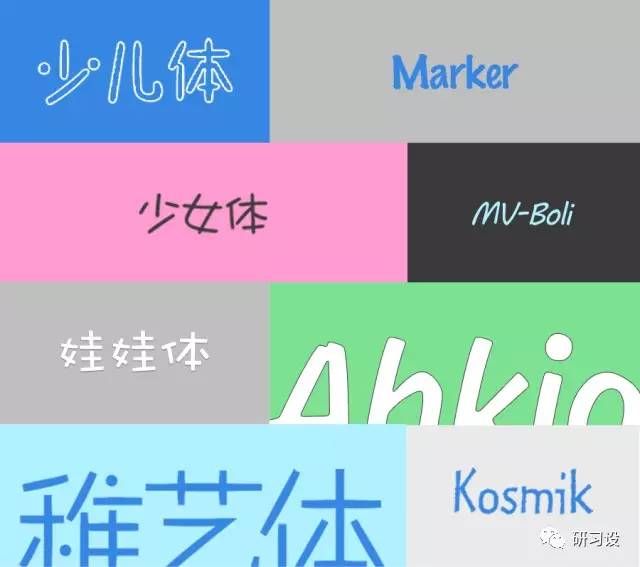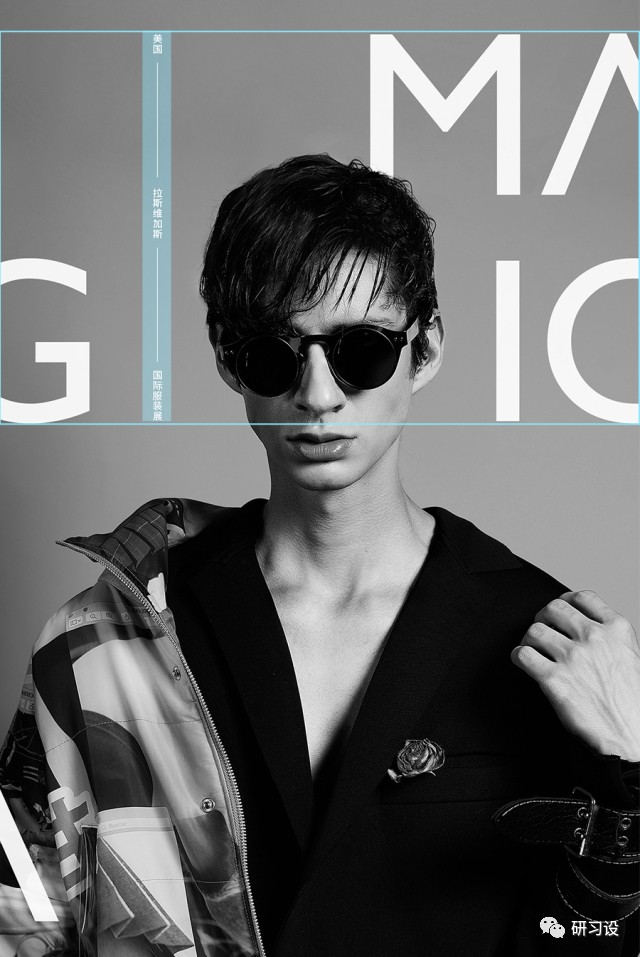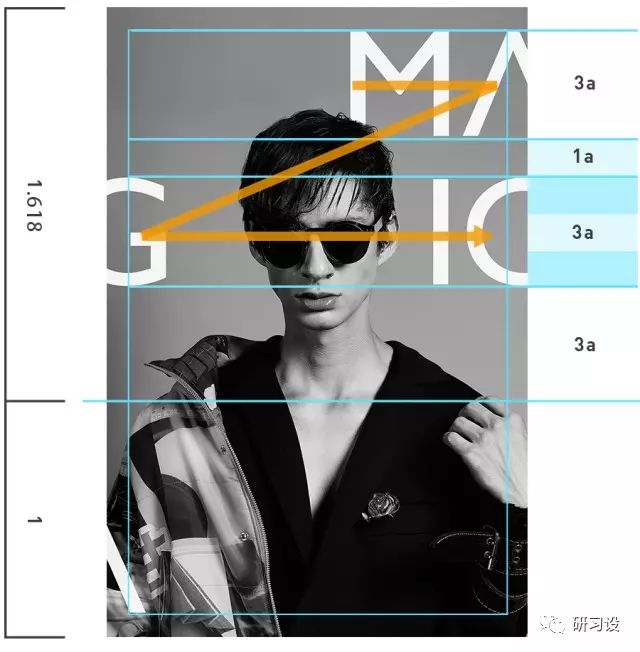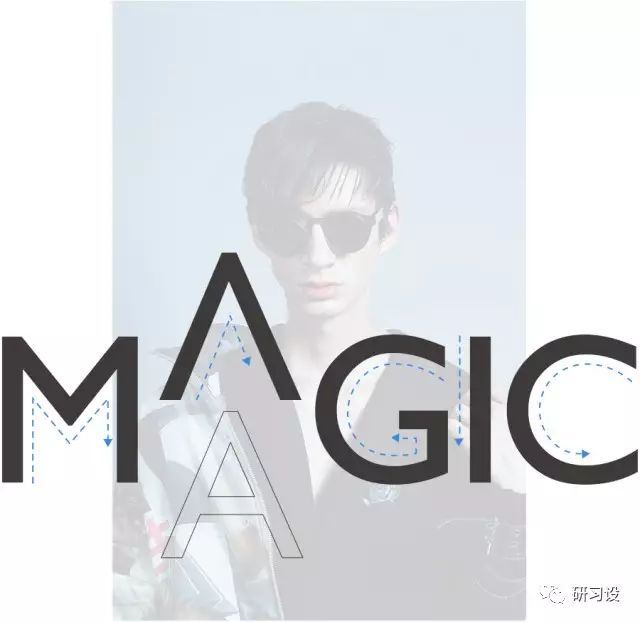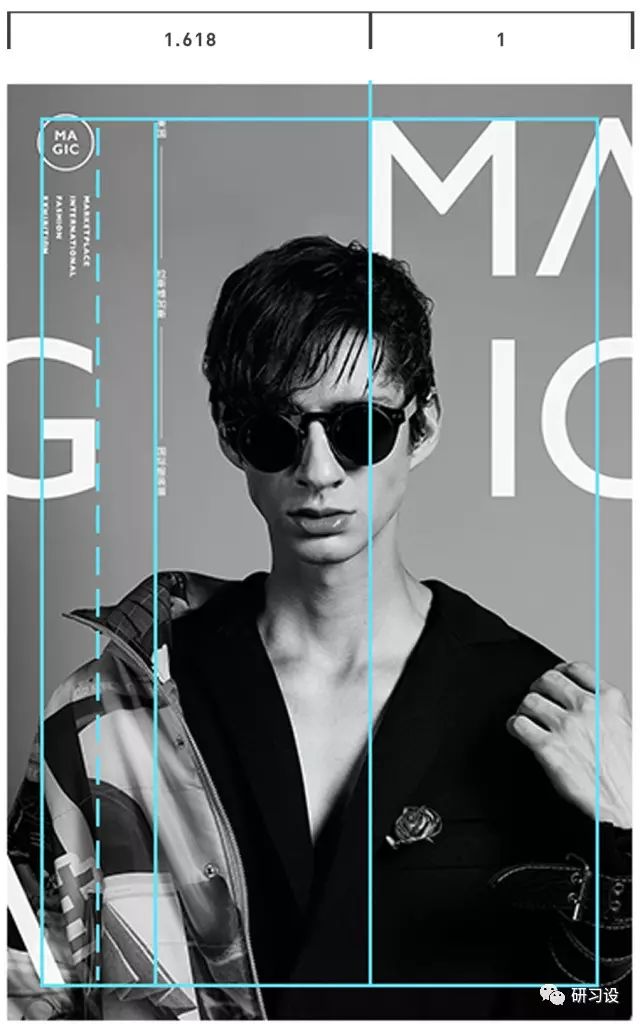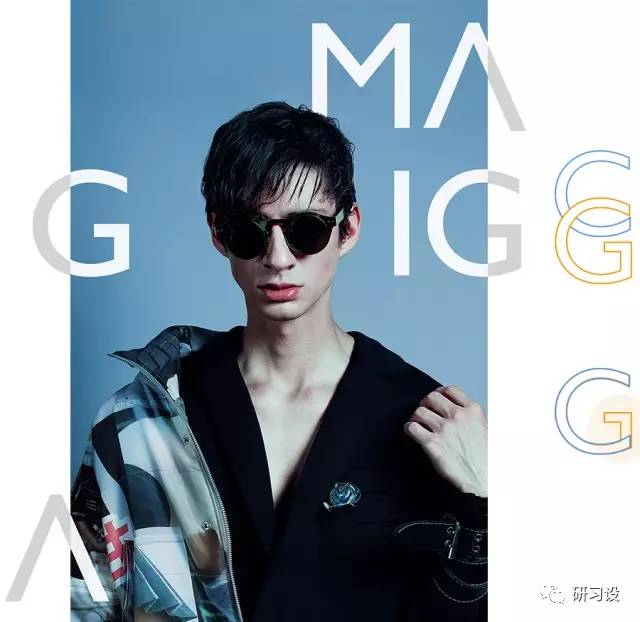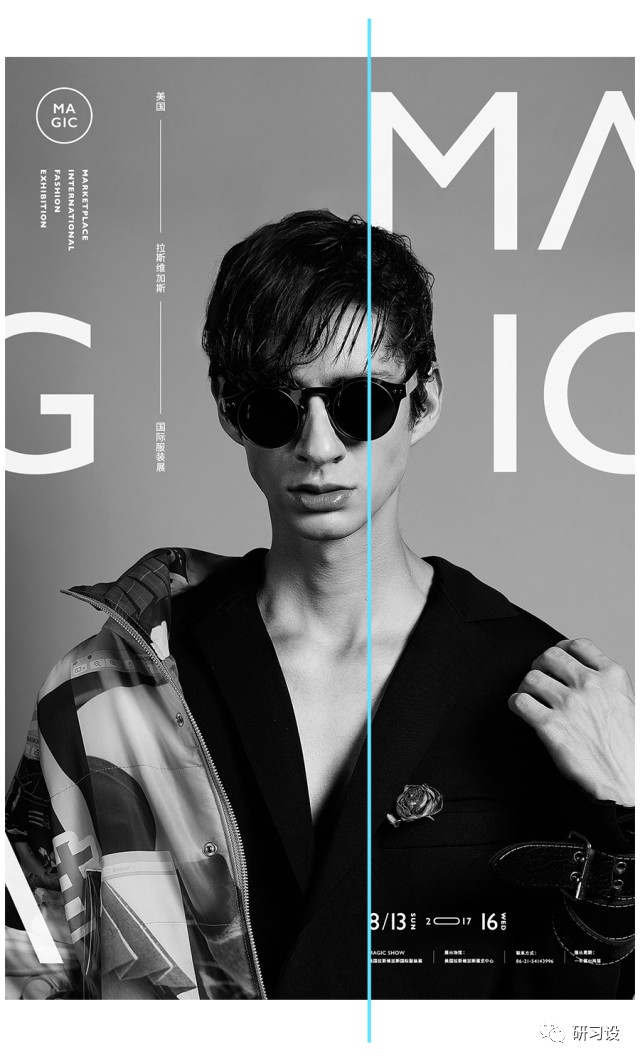
如何搭配字体?一篇文章教你轻松学会搭配字体
每一种字体都有其不同的面貌与适用情境,拿电影举例,古装电影除需要演员的服装与场景符合情境外,配乐与字体也都需要统一风格,以符合特定时代背景的整体氛围。设计亦是如此,本期将为大家介绍字体的大致分类以及不同情境下适合表现的字体有哪些。
其中我们会试图解释为什么这种字形会给人这样的印象,以及对大分类下的字体进一步细分,如:不同的黑体在气质表现上都有哪些区别?它的应用场景有哪些?想要知道这些疑问的话,就请继续往下观看吧!
字体的分类其实并没有一个官方的标准,但各种分类方式的基本原则是相同的,这里为了方便理解,将西文与汉字之间具有共通性的字体类别相结合对应,一共大致分为以上五类。
字体的应用场景大致来说一共有两种用途,一种是以少量字数出现的标题用字,以及大面积出现的正文用字。对于标题用字来说,更加强调易认性,字形设计往往张力较大细节较多,以达到抓眼球的目的。而针对正文的字体设计,更强调易读性,字形变化性较小,除正文用途外也可以在标题中使用,是普遍使用的字体。
与大家玩个游戏,当我们看到下方的图片时,哪些会给你想去亲近和触摸呢?又有哪些图片会让你觉得危险想远离它呢?在心中默默选择好后我们接着往下看。
在现实生活中,尖锐的钉子、刀尖、破碎的玻璃,这些都会划伤皮肤,而在大自然中,植物的尖刺与锋利的石头也同样是危险的。这些经验与记忆每时每刻都在影响我们的感受,让我们对事物产生同形联想,当人们看到这类物体,视觉心理上会产生紧张感,而外表光滑圆润的物体多数是安全无害和易于接近的。所以说,上图中能够传达亲近感与可爱印象的图片应该是编号②④⑤。
在字体中,同形联想依然存在,中文的圆体是从黑体字逐渐演化而来,结构上继承了黑体的工整大方。笔画的末端圆润,给人易于亲近的印象。随着笔画的粗细变化,字体的气质也会随之变化,粗笔画的圆体字会呈现出儿童与幼稚的印象,笔画越细,则会越显成熟。
在西文字体中的圆体,也是根据无衬线体演化而来,气质的变化与中文圆体类似。因为西文的字母笔画相对于中文来说要少,结构上也更加简单,所以在粗细的变化的幅度上会较中文圆体的粗细幅度更强烈一些。
如今数码字库中的字体,就像工厂中批量生产的罐头一样,非常的规范,传递出冰冷的机械感。而人为手写的文字则因为笔画书写的不规则痕迹给人温暖自然的感觉,更加具有生命力。
想要让字体传递出亲和力,我们就需要选择具有手写特征的字体,这种字形会更具人文气息。不同的手写字体会呈现出不同的亲和力,笔画轻松自然的手写体用在休闲的情景中较为合适,像西文这种铜版手写体 ⎾ 西文花体 ⏌ 则表现的更加正式与高级。
针对表现儿童的字体,他们的共同点都是具有手写的特征,而在笔画末端多数呈现圆滑的形状。这里需要注意的是,我们不能根据自己的喜好而随意应用儿童体,对于青春期的少女或者表现小孩时,我们使用儿童体并不会有什么问题,但是如果出现在政府的对外形象或本应体现端庄的场景,就不是那么合适了。
下图中,哪些图片会给你现代的感觉?哪些又会给你自然的印象呢?仔细想想这背后的原因之后,我们继续往下看。
所谓的现代感,其实就是自然界中找不到的,人们通过解构大自然,运用几何与线条人为创造出的物体。它是符合当今时代流行的趋势的,在工业、音乐、服装、建筑等各个领域都有体现。上图中符合现代感的图片是编号①③⑥。
我们以建筑举例,与崇尚自然的装饰风格不同,现代风格更加抽象与几何化。对于字体来说,文字的构成越简单,越会给人简洁抽象的印象。虽然会觉得缺少生命力,但也会呈现出现代感与先进的印象。
中文字库中的黑体,相对宋体来说笔画特征会更加简洁,几何的造型结构给人现代的印象。而在黑体分类中,并不是所有的黑体都绝对是水平垂直的结构,早期的黑体,中宫较小,笔画结构存有手写特征,喇叭口更是在照排时期为保证笔画边缘的锐利程度而特别设计的。这种黑体更适合表现与人文相关的情景,相对于老式黑体,现代黑体中宫更大,在小字号下更加容易识别,是效仿西方文字的理论而设计出来的,更适合表现现代感的情景。
无衬线体与中文的黑体类似,同样具有人文主义结构与现代几何造型等不同的字形。人文主义字体结构中保留了手写痕迹;而现在主义的字体更加几何化,适合表现现代感相关的情景;处于两种风格之间的字形则相对中性,没有明显气质,因此适用范围较广泛。
西文相对于中文来说,笔画更加简单,我们选用几何造型强烈的展示性字体同样能够表现出未来与先进的印象。这里需要注意的是,文字的造型越倾向于图形化,辨识度也就会随之降低。所以在使用这类字体时需要格外谨慎,它仅适用于标题或版面中的主形象等场景。
文字是人类文明发展的重要标志,其演变见证并记录了世界的文明发展历程。下图展示的是几种古老的文字发展源头,它们分别是苏美尔人的楔形字、古埃及的圣书字以及古中国的甲骨文。了解文字的演变过程,会更有助于我们接下来的讲解。
中国的汉字起初由雕刻在龟甲与牛骨之上的甲骨文逐渐演变到雕刻于钟鼎上的金文,又从金文演变成为大篆小篆,而隶变的发生是古今汉字的分水岭,它是篆书为了解决快速书写的需求而逐渐简化形成的。又从隶书的快速书写的过程中形成了草书,草书经过楷化,更加规范和端正,而行书介于草书与楷书之间,弥补了楷书书写速度过慢和草书不易识别的问题。在选择书法字时,需要与所传达的项目背景相对应。越古老的文字,其历史感越强。
在汉字的印刷体当中,宋体字是历史最为悠久的字体,在表现文化与历史感时,除书法体外,宋体则是最佳选择。
在汉字的宋体字中,老式宋体的笔画结构带有手工雕刻的痕迹,中宫较小,重心偏高,适合表现文化与历史相关的情境,又因为这种历史感,会给人传统、正统与高格调的印象,所以也能传递出高级感;而现代宋体笔画呈几何化结构,相对于老式宋体的温情,现代宋体更加的冷峻,具有时尚感与精致的印象;处于两者之间的中间型宋体,同时具有两者的优缺点,是现今比较通用的宋体字形。
衬线体是最能体现出历史感的字形,起初只有23个大写字母,直到十六世纪才逐渐补全26个。衬线是在雕刻前通过方头笔书写时自然形成的。
衬线体中,带有手工感的老式衬线体,适合表现文化与历史感;现代型衬线体,笔画呈几何结构,适合表现时尚与高格调的印象;处于两者之间的是过渡型衬线体,是常用于正文与标题的通用性字形。(如继续细分,可以分为老式衬线/复古衬线/过渡衬线/现代衬线/粗衬线)
根据风格定位与文案信息所需要体现的情境,我们选择西文中的具有现代感的无衬线体来与之匹配。并根据定位拍摄照片或去图库中寻找符合要求的照片,经过观察发现,上图五个拉丁字母中只有A的笔画具有封闭性,这里我们可以将之替换成希腊字母中的 Λ ,这在英语环境中并不会过于影响它的识别性,也是比较常见的处理形式。
接下来我们将选择好的照片与字体进行组合搭配,除字体与照片的选择之外,在排版形式上也需要偏向现代感。这里为了让画面显得更丰富,将字母拆解后置入到版面中,并做出血处理。而出血之外的部分会重复的出现在版面中,以体现数码风格的这种特性。版面中C与G的外观轮廓极为相似,只需要将G的特征部位裁切掉就可以识别成字母C,而左下角的斜线并不具备识别性。它仅作为与上方图形呼应的补充。
主标题的位置与比例大致确定好以后,我们可以借助一些美学比例来微调版面中元素的位置关系。这里文字虽然是以散布的形式出现,但基本的Z型视线引导原则还是需要遵守的,也就是说,字距需要小于行距,并以从左上到右下的阅读逻辑来编排文字元素。
主标题的位置确定好后,接下来添加其他信息,将展览名称添加到主标题的空白位置。这里中文的字型,我们选择具有现代感的黑体。呈几何造型的黑体可以与现代型无衬线体毫无违和的搭配在一起。
左上角还有一些空,我们将图标与英文信息添加到版面中,注意元素的交叉对齐,这里将组合与字母G的转折处对齐。
在版面底部将时间与地址等信息依次编排到版面中,并与主标题的M对齐。文字注意比例的大小与层级关系。再保证版面平衡的基础上编排文字。
最后,将剩下的剩余的信息置入版面中,与中线呈水平对齐,经过微调后,这个版面就完成了。
主题名称是“不朽的梵高”从语义来说,这是一个需要表现复古与文艺的印象,我们选择老式风格的宋体字形作为基础,为了更好的传递这个概念,我们可以进一步刻画主标题,将它处理成经岁月侵蚀而残缺的外形。使其更加接近图形的印象,创建记忆点。
可以使用简单的方式实现这个效果,大致思路是将字体通过高斯模糊命令处理成虚化的状态,并在文字底部合并白底色图层,再通过色阶命令来调整黑与白之间的关系,以达到最佳效果。
将处理好后的主标题置入到版面中,并根据图像本身的内容来决定文字编排的位置与形式,这里我们将主标题文字竖排摆放在版面的右侧。梵高是巴洛克时期的代表画家,我们可以选择巴洛克时期的过渡型西文字体来与版面搭配。接下来我们加入二级文字信息,这里需要注意的是,文字组合与人物的呼应关系。
接下来加入内文信息与时间信息,通过大中小的层级加入到版面中,同时需要注意版面的平衡与对齐以及留白的完整度。
最后,加入点缀性元素,通过美学比例微调版面中元素的位置关系,这个版面就完成了。
我们知道了汉字与西文的大致分类,了解了正文与标题之间的关系与特点,也知道了各个字体的气质与所适合表达的情境有哪些。这里虽然仅举了三种情境,但相信大家也已经了解了这其中的规律与分析气质的方法了,为版面搭配适合情境的字体,是一名合格设计师应具备的基本能力。